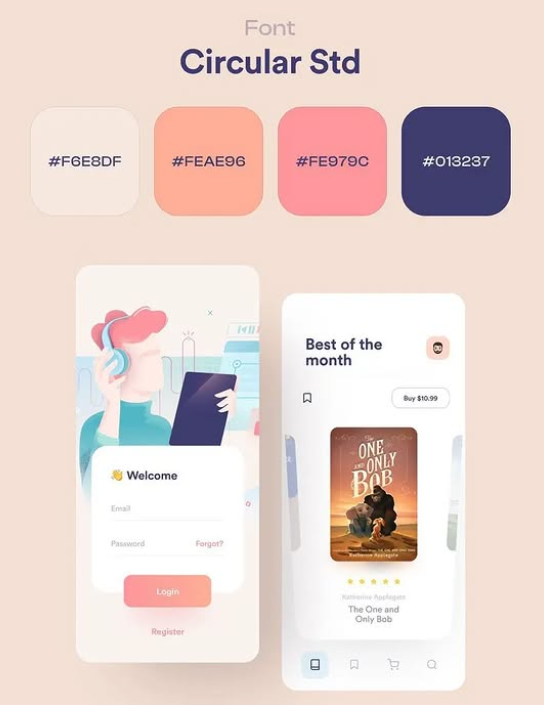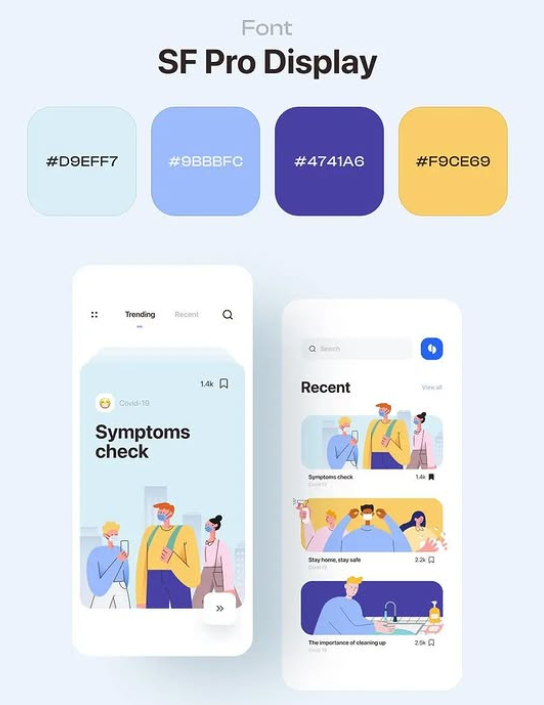
5 Kombinasi Warna dan Font untuk Desain UI
Perkembangan teknologi memiliki pengaruh besar dalam perkembangan style desain grafis terutama untuk kebutuhan desain media digital. Desain UI untuk website dan aplikasi digital harus dirancang dengan cermat agar efektif untuk menarik perhatian dan memberikan kenyamanan bagi pengguna. Kombinasi elemen visual seperti warna dan font dalam desain UI harus harus harmonis dan diatur dengan baik agar menarik.
Prinsip dasar desain grafis seperti kesatuan, kontras, hirarki visual dan lainnya harus dimanfaatkan dalam menyusun desain UI. Pertimbangkan kebutuhan elemen visual yang menciptakan desain visual menarik tetapi juga memberikan kenyamanan selama mengakses website dan aplikasi. Font dan warna termasuk elemen penting dalam membuat informasi dan konten desain UI menjadi menarik.
ELEMEN VISUAL DALAM DESAIN UI
Pada dasarnya desain UI untuk website dan aplikasi digital akan menggunakan elemen-elemen visual dalam desain grafis pada umumnya. Elemen visual seperti warna, tipografi. ilustrasi dan berbagai prinsip dasar desain berperan penting dalam menciptakan desain yang menarik dan ramah pengguna. Penting untuk memilih elemen visual yang cocok untuk media digital sehingga menciptakan desain visual yang efektif.
Secara umum desain UI akan memiliki ciri elemen visual yang seperti:
• Tipografi sederhana dan bersih: Font harus memiliki desain sederhana dan tampil bersih agar teks dalam konten mudah terbaca dan efektif menyampaikan informasi.
• Warna yang kalem dan netral: Penting untuk memilih kombinasi warna yang harmonis dan memberikan kenyaman untuk mata audiens. Warna juga harus kontras agar teks mudah terbaca dengan menggunakan warna netral dan kalem.
• Ilustrasi menarik dan sesuai tema desain: Desain UI juga harus memiliki elemen visual berupa gambar ilustrasi yang relevan. Gambar ilustrasi harus membantu meningkatkan daya tarik visual desain UI.
• Menerapkan prinsip dasar desain grafis: Agar konten dan elemen visual dalam desain UI menarik dan efektif, penting untuk menerapkan prinsip dasar untuk menciptakan layout desain visual yang memikat.
TIPS MEMILIH WARNA DAN FONT UNTUK DESAIN UI
Desain grafis untuk UI akan mempertimbangkan penggunaan elemen visual yang efektif dalam media digital. Elemen visual seperti warna dan font dalam desain UI harus dipilih dengan bijak agar harmonis dan menciptakan kenyamanan pengguna. Perhatikan beberapa tips ini untuk memilih kombinasi warna dan font desain UI yang tepat:
Warna Harus Harmonis
Dalam menciptakan desain UI warna harus memiliki kombinasi yang harmonis agar desain visualnya terlihat menarik. Desain UI yang memiliki warna harmonis akan terlihat profesional dan menarik perhatian.
Gunakan warna netral sebagai warna base agar kombinasi warna harmonis. Selain itu gunakan skema warna untuk menyusun warna yang harmonis seperti warna analog dan monokrom. Kombinasi warna yang harus bisa mengambil dari tema brand atau karakter merek.
Warna Tidak Membuat Mata Lelah
Kombinasi warna dalam desain UI juga harus berhati-hati agar tidak memilih kombinasi warna yang membuat lelah. Kombinasi warna yang buruk untuk desain UI bisa membuat mata audiens cepat lelah jika menggunakan website dan aplikasi dalam waktu yang lama.
Hindari menggunakan kombinasi warna yang terlalu kontras dan mencolok. Jika ingin menggunakan warna komplementer pastikan mengatur saturasi warna agar harmonis. Warna yang dominan harus menggunakan warna yang membuat mata nyaman.
Warna Meningkatkan Keterbacaan Informasi
Pastikan juga untuk memilih warna yang bisa meningkatkan keterbacaan teks, kejelasan konten dan gambar. Biasanya agar teks terbaca dengan baik dalam desain UI, maka bisa menggunakan teks dengan warna netral. Warna latar belakang dan teks harus kontras agar teks memiliki keterbacaan yang baik. Biasanya warna teks akan menggunakan warna hitam atau putih untuk meningkatkan keterbacaan, dan pilih latar yang kontras.
Tipografi yang Sederhana dan Bersih
Desain UI umumnya akan memiliki gaya tipografi sederhana, pilih jenis font yang memiliki desain sederhana dan bersih. Pilih font sans serif atau serif untuk desain UI agar berbagai konten dan informasi terbaca dengan baik. Gaya font yang sederhana akan efektif untuk media digital, termasuk dalam berbagai ukuran dan jenis perangkat.
Memiliki Font Judul dan Paragraf Kontras
Dalam desain UI jangan hanya menggunakan satu jenis font saja, kombinasikan dua atau tiga font yang harmonis. Kombinasikan font yang kontras tetapi harmonis dan sederhana untuk menciptakan hirarki visual.
Biasanya font judul akan memiliki font tebal dan memiliki ukuran besar, sementara paragraf akan efektif menggunakan font yang lebih sederhana dan tipis. Pastikan font kontras tetapi masih memiliki keterbacaan yang baik agar tetap relevan.
Kombinasi warna dan font untuk desain UI harus dipilih yang harmonis, sederhana dan menciptakan kesan nyaman. Warna yang digunakan juga perlu relevan dengan brand agar menjadi identitas yang kuat. Font yang digunakan dalam desain UI biasanya yang memiliki style sederhana dan yang konsisten. Kombinasi font dan warna harus harmonis dan memberikan kemudahan audiens dalam menjelajah konten website dan aplikasi.